海报字体设计非常的关键,不同的字体都是由人工来设计完成的,汇聚了多位字体设计师的心血,想要开发出一套精品字库,设计出一套比较有艺术感的字体,需要耗费的心血非常的多。
海报字体风格也比较多,每一款字体风格都会有不同的艺术表现,比如说有的字体风格会秀丽柔美,给人的感觉非常舒适,尤其是字体在线条上很流畅,让人立马就有一种优美清新的感觉。但是有的字体风格则是比较活泼有趣的,像这种字体风格就比较适合于儿童用品或者是一些比较具有时尚感的产品海报。而字体比较苍劲古朴,那么就很适合一些民间艺术品的宣传海报,这种字体风格会更容易让人产生怀旧的感觉,有一种朴素无华的美感。更多字体可以选择海报广告字体转换器来进行。
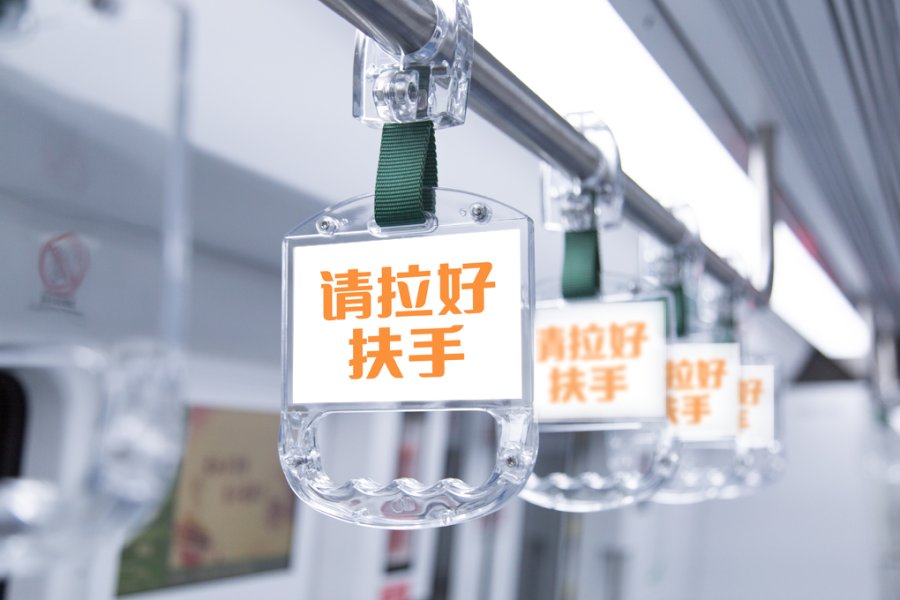
海报字体制作并不困难,选择字体的时候可以选择专门的字体设计软件来完成设计。如果是初学者,那么首先需要在设计的时候借助原有的基础,对现有的字体造型进行修改,然后设计出不同风格的字模。印品字库觉得不同字体海报的特点也是不一样的,但不管是哪一种特点,最主要的就是为了能够吸引别人的关注,吸引读者的关注,所以需要字体的艺术表现力非常强,这样才能够达到吸引人的目的。